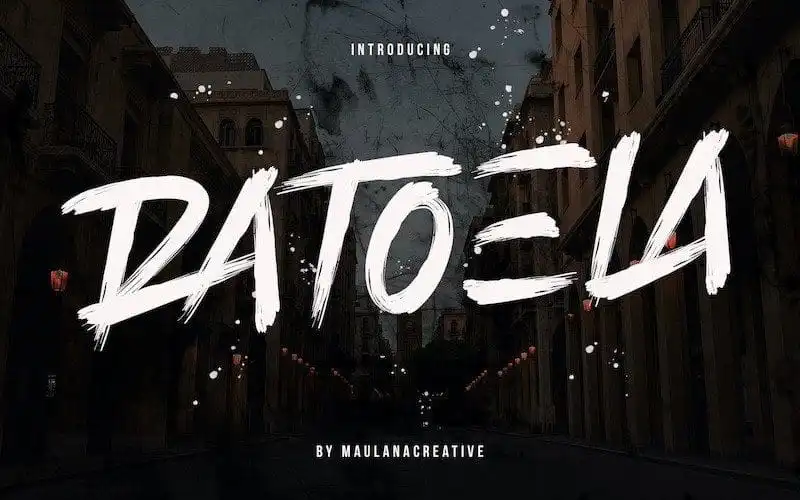
Ratoela Brush Font – Download Grátis
Introduzimos a Ratoela Brush Font, uma fonte criada por Maulana Creative que mescla desenhos bruscos com curvas atrativas e um toque urbano moderno. Esse design robusto e cheio de vida é perfeito para criar mensagens singulares, embalagens ou rótulos de livros, capas de revistas, sites, identidades visuais, roupas, marcas e embalagens. Não apenas complementa a sua coleção atual de fontes, mas também se torna um aliado ideal para designers que buscam uma combinação única e moderna em suas criações. Este é o tipo certo para dar ao seu design aquela pitada especial.